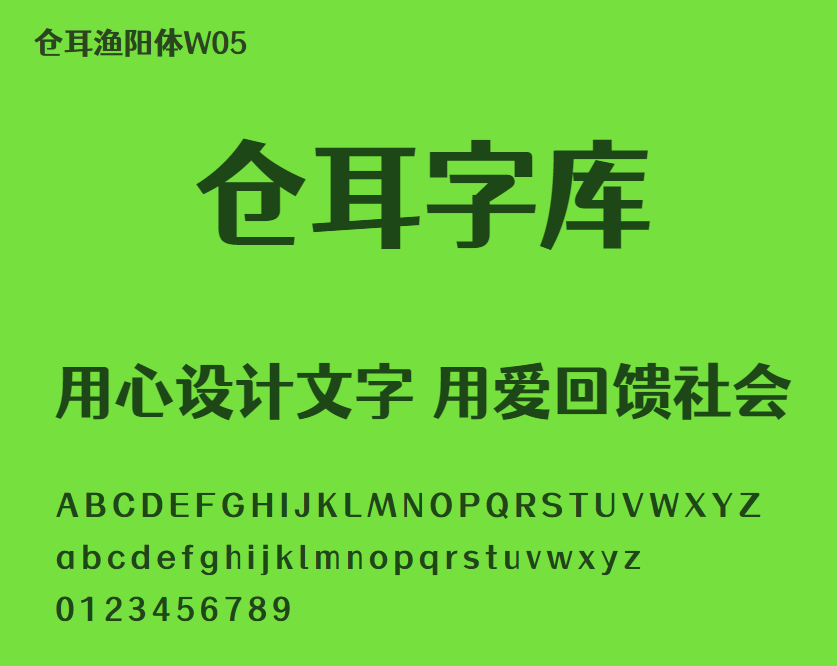
仓耳渔阳体W05
仓耳渔阳体W05,这款字体结构工整、笔画清晰,兼顾美观与易读性,适用于标题、正文、海报、包装、LOGO 等多种场景。字形优雅稳定,风格百搭耐看,适配日常排版与创意设计,让文字呈现更舒适、更具质感。仓耳渔阳体W05一笔一画,皆是细节,以均衡的比例、流畅的线条打造舒适视觉体验,字形端正大气,风格简约现代。无论是商业设计、品牌宣传还是日常排版,都能轻松驾驭,让文字更有格调与力量。仓耳渔阳体W05字体下载。